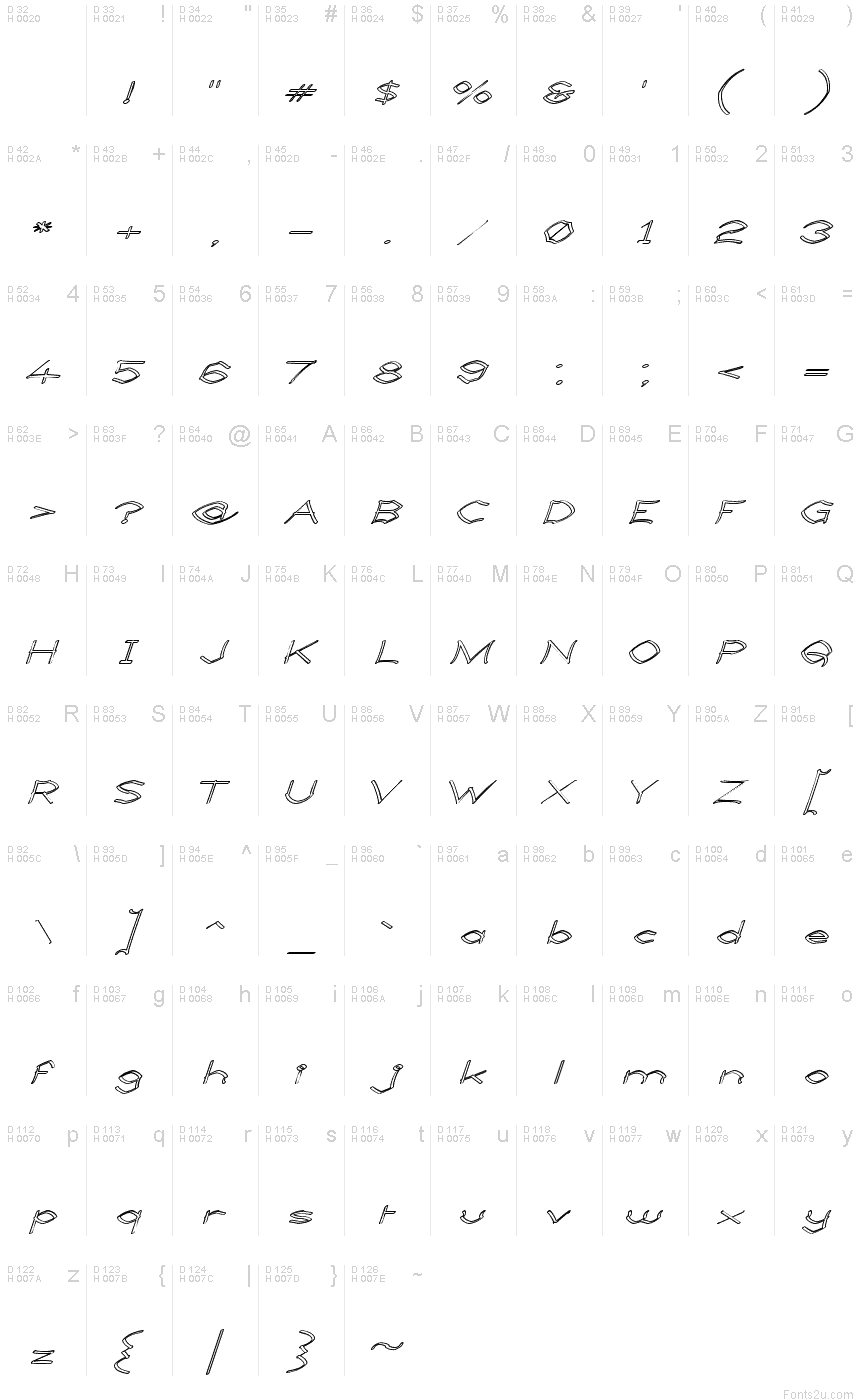
GemFontsによるLlynfyrch Fwyrrdynn Oulineは、手描き風のダブルライン構造とわずかに不規則な輪郭が特徴のレトロなディスプレイフォントです。文字は軽やかなアウトラインを保ちつつも、揺らぎのある曲線や角張ったターニングが、まるで手描きされたかのような質感を醸し出しています。
Llynfyrch Fwyrrdynn Oulineは、クラフト感のあるレトロなタイトルデザインが必要なポスターのタイトル、ロゴ、アルバムジャケット、パッケージ、イベントフライヤーなどに最適です。オープンなアウトラインはレイヤーや装飾を加えやすいため、装飾的な看板、テーマ性のあるカバーアート、インディープロジェクトのラベルなどにも自然に溶け込みます。
Llynfyrch Fwyrrdynn Oulineフォントの文字一覧
Llynfyrch Fwyrrdynn Oulineフォントのグリフ — 基本ラテン文字、1ページ目